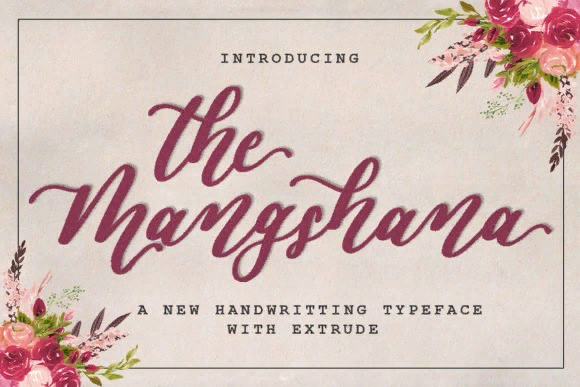
[Creativefabrica] The Mangshana Font (2021)
Mangshana - это элегантный шрифт с современной атмосферой и безупречной формой, вдохновленный нестареющей классической каллиграфией.
Не слишком тонкий и не слишком толстый, сбалансированный и разнообразный, этот шрифт создан для того, чтобы подчеркнуть красоту ваших проектов.